Figmaを利用するなかで課題に感じていたのが、和文と欧文に対しフォントを個別に設定できない点です。この課題を解決するため、『Japanese Font Mixer』というプラグインを開発しCommunityで公開しました。あわせてソースコードもGitHubで公開しています。
本記事ではプラグイン自体の機能とプラグイン開発に至る経緯を説明します。
プラグインについて
『Japanese Font Mixer』では和文と欧文に対してワンクリックでフォントを設定できます。
また、和文全体だけでなく漢字・かな・約物といった文字種別ごとにフォントを指定することもできます。
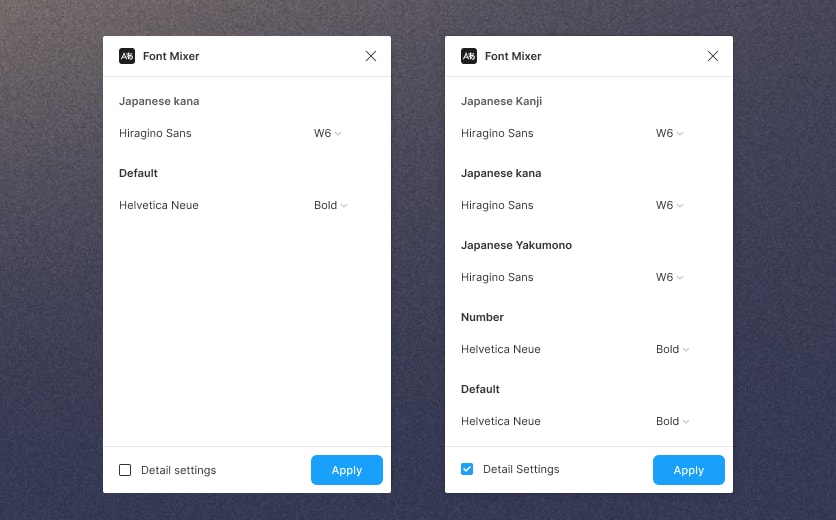
たとえば次のような指定が可能です。
- 和文は『ヒラギノ角ゴシック』、欧文は『Helvetica』
- かな・漢字は『ヒラギノ角ゴシック』、約物は『Yaku Han JP』
後ほど言及しますが、FigmaではTextLayerの中の文字に対してフォントを指定するには文字を選択していちいち設定する必要がありますが、本プラグインを利用することで一括でフォントの指定が可能になります。
また、日本語のウェブサイトを作る場合、和文・欧文で別のフォントを当てることがあるのでより実態に近いモックを作ることができます。
デザイン以外の用途で言えばFigmaでスライドを作る方もいるようですが、そういった場合も便利に使えると思います。
なぜ作ったか
KODANSHAtechのデザイナーチームでは毎週『デザイン分科会』というミーティングを設定して、デザイントピックについて話し合っています。その中で「和文・欧文の混ざりのテキストレイヤーでは和文のフォントを当てがちだよね」という発言がありました。実際のウェブサイトでは和文・欧文では個別のフォントを設定しているため、Figma上のデザインの印象とずれてしまうのです。
CSSでのフォント指定ではOSごとに利用されるフォントが変わることがあるので、見た目が完全に再現されるわけではありません。個人的には日本語フォントを指定した時の従属欧文がもっさりしているのが非常に気になります。
この課題を解決するために軽くプラグインを調べてみましたが、その時点で見つけたプラグインは使い勝手が悪く、作り直したほうが良いものになりそうな印象を持ちました。
またプラグイン以外の選択肢も検討して、事前に和文・欧文を混ぜたフォントを共有して使えないか?と思いましたが、フォントのライセンスがややこしいのと、Figma上のチーム上でフォントを共有するにはビジネスプランへの加入が必要(弊社ではプロフェッショナルプランを利用しています)なこともあり断念しました。
そこで、月に2日まで業務に直接関係ない研究・実験を行えるKODANSHAtechの『R&Dデー』制度を利用してプラグインを開発することにしました。開発1日目でコア機能は完成し、2日目にプラグインのUIをFigmaのUIに近づける作業を行いプラグインの公開にこぎつけました。
おわりに
普段の業務で課題に感じたことを、短い期間で解決することができたのはとても良かったです。ある程度ウェブフロントエンド開発の知識があればFigmaプラグインの開発は簡単だったので、欲しいものがなければ自作するのは十分選択肢になりそうです。
現状公開しているものは、その場でフォントを指定して適用するだけのシンプルな機能になっています。本当は複数のスタイルを登録して出し分けれれば便利かなと思いましたが、現状のままでも十分利用に耐えると思っています。Figmaコミュニティで、さらなる機能要望があれば実装していこうと思っています。